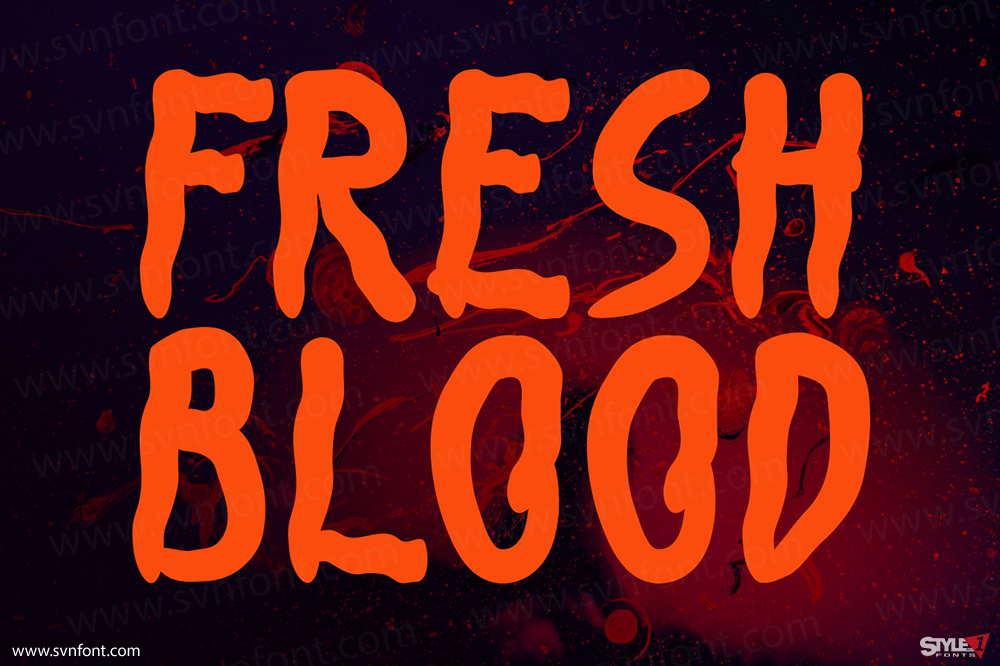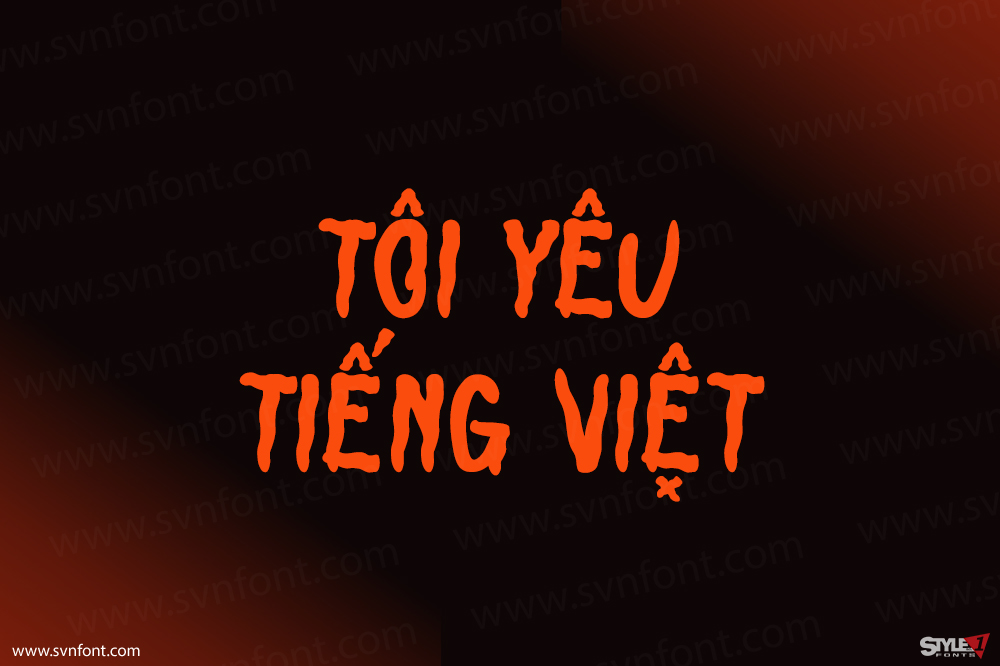
Basement Horror là một phông chữ hiển thị được thiết kế đặc biệt để tạo ra một bầu không khí ma quái, bí ẩn và thể hiện tinh thần của lễ hội Halloween. Phông chữ này có thể được sử dụng trong nhiều phương tiện truyền thông liên quan đến Halloween, chẳng hạn như thiệp mời dự tiệc, áp phích, thiết kế hàng hóa, thiệp chúc mừng, biển cảnh báo hoặc trong thiết kế trang web có chủ đề Halloween.
Nhà thiết kế: Maikohatta
Nhà phát hành: Maikohatta